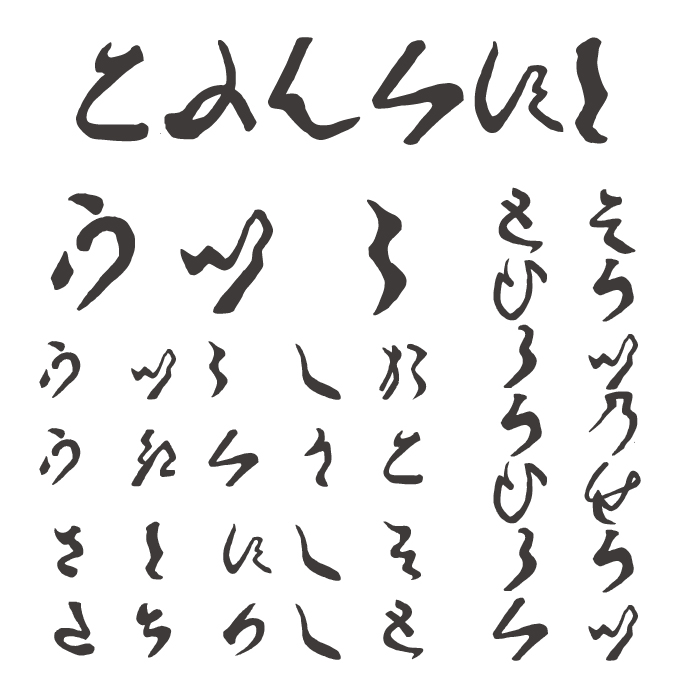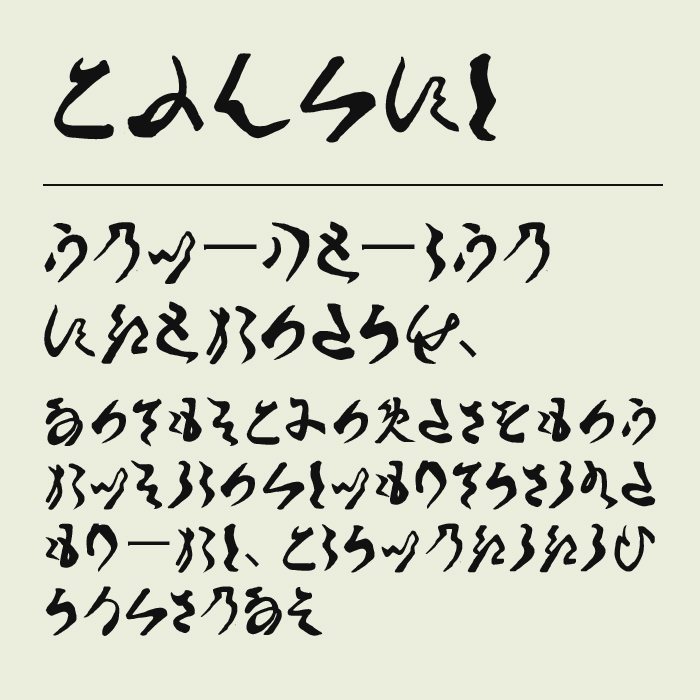
古文書崩し字かなフォントは、力強い筆致と実際に古文書の中で使用されているひらがなをフォント化した筆文字風フォントです。
大きく跳ねたり止めたりする筆の運びが個性的で、まるで江戸古文書の手書きの勢いそのままを写し取ったような文字が再現されている感があります。
フォントの文字見本
収録文字は、ひらがなが収録。